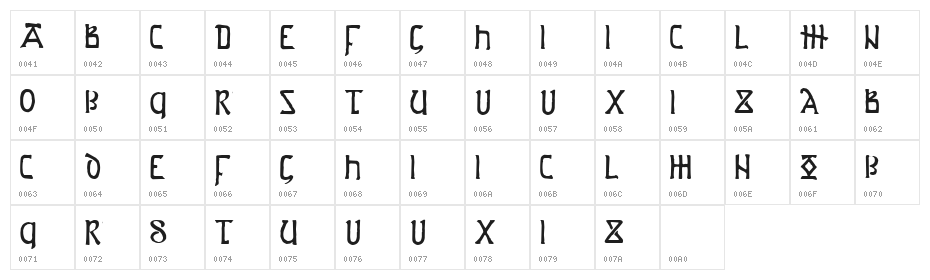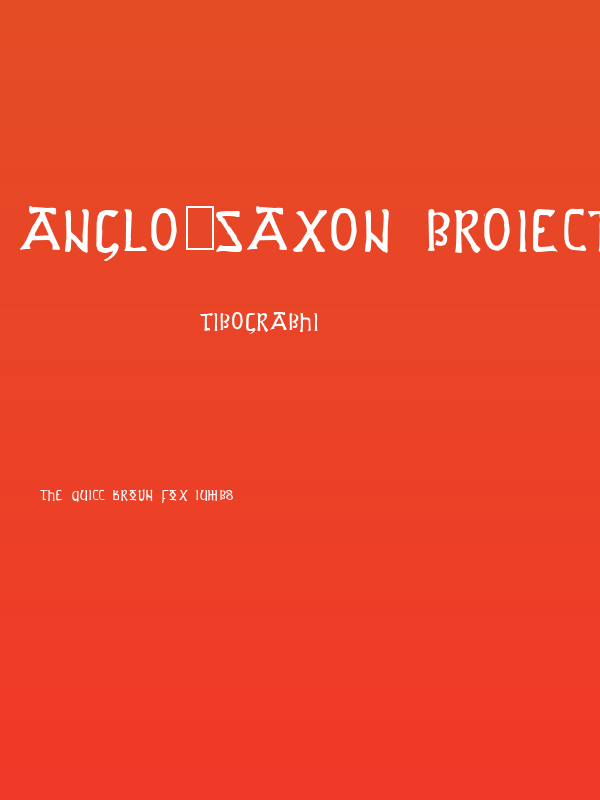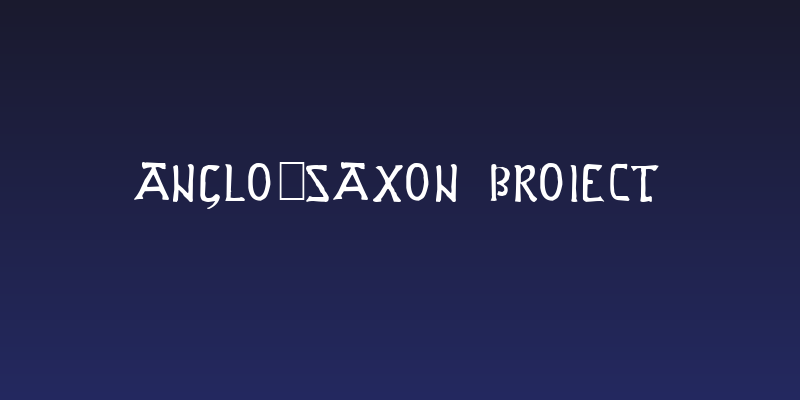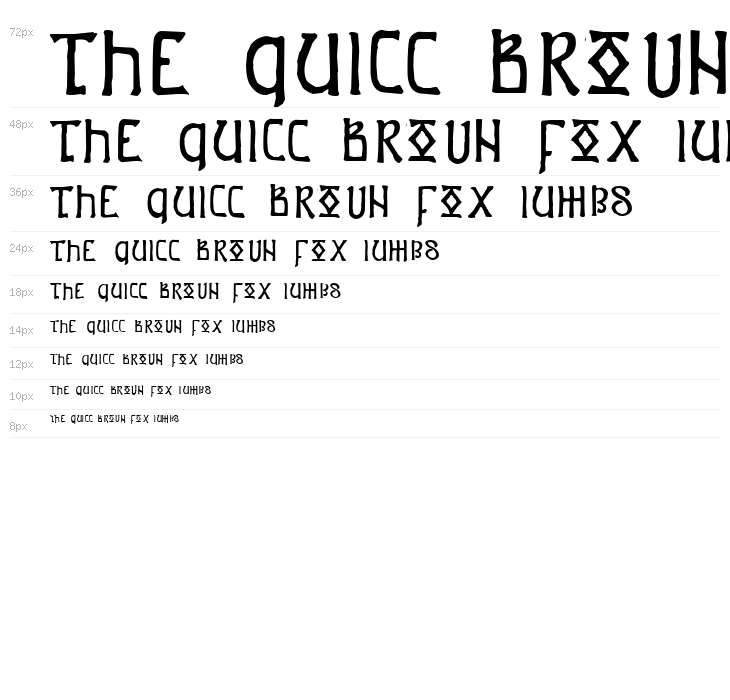
Anglo-Saxon Project Font
| Progetti proposti | Perfect for historical reenactment posters, medieval-themed events, fantasy book covers, or video game interfaces set in ancient times. |